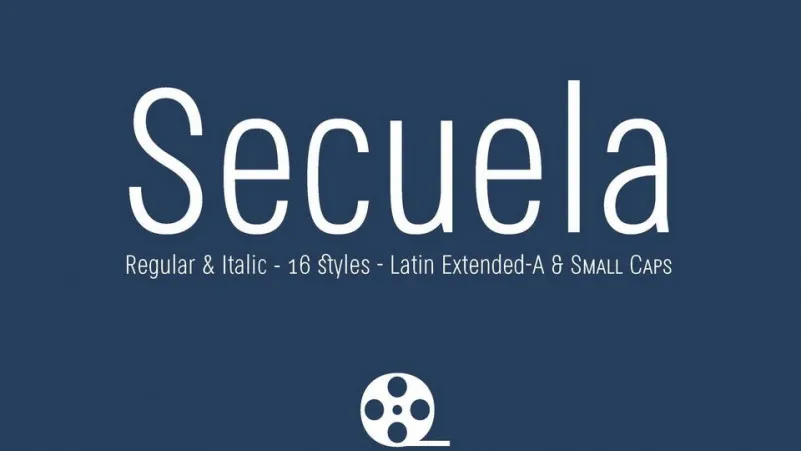
A Secuela Font é uma elegante escolha para designers que valorizam modernidade e simplicidade. Ela é uma nova abordagem para o tipo sans-serif, com linhas retas e caracteres geométricos que permitem um olhar fresco e contemporâneo sobre a tipografia. Embora seja um tipo geométrico e de estilo neo-gótico, sua aparência é acolhedora graças aos arredondamentos suaves em seus traços, o que evita qualquer frieza que possa surgir nas tipografias puramente grotescas. Este tipo foi projetado para combinar harmoniosamente tanto com textos quanto com assinaturas ou headlines, adequando-se perfeitamente para ambientes de impressão e tela. Sua aparência elegante e amigável faz dela uma opção popular para qualquer tipo de projeto visual em que desejas transmitir um toque moderno e personalizado.